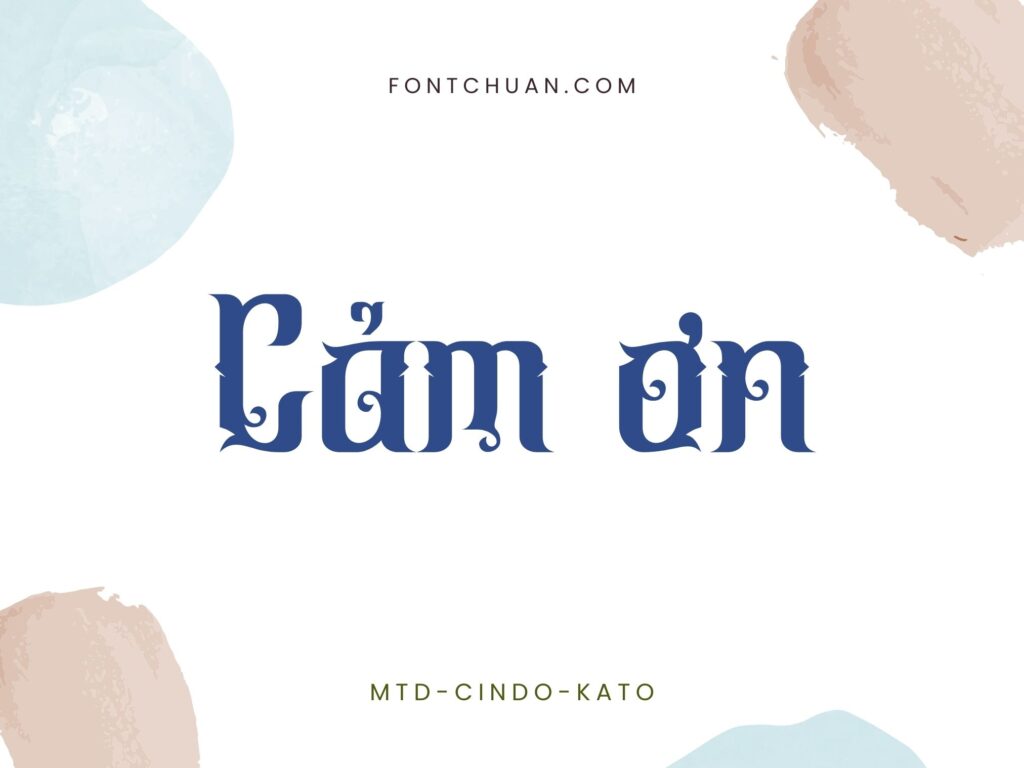
Font MTD Cindo Kato là một kiểu chữ trang trí độc đáo, được thiết kế với phong cách hiện đại và sáng tạo. Font này hỗ trợ đầy đủ tiếng Việt cùng hơn 90 ngôn ngữ khác, mở rộng khả năng ứng dụng trong các thiết kế đa ngôn ngữ. Đây là một trong những phông chữ được cộng đồng thiết kế đánh giá cao và sử dụng trong nhiều dự án sáng tạo, đáp ứng nhu cầu đa dạng của người dùng.
MTD Cindo Kato nổi bật với các đường nét mạnh mẽ và phong cách độc đáo, tạo cảm giác hiện đại và năng động. Font rất phù hợp cho các thiết kế logo, tiêu đề, bao bì sản phẩm, thiệp mời và các ấn phẩm đòi hỏi sự sáng tạo và khác biệt. Các ngành nghề phù hợp bao gồm quảng cáo, giáo dục, công nghệ, thiệp cưới và ảnh cưới. Font này cũng lý tưởng cho các sự kiện như Tết, Giáng sinh, Valentine và các lễ hội khác.